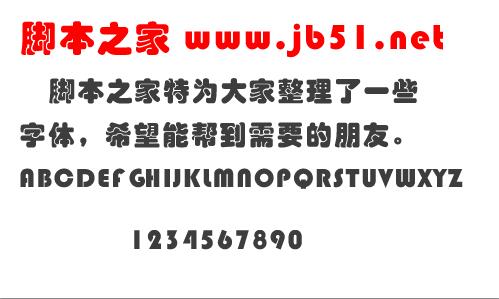
微软简琥珀体
微软简琥珀字体是一款十分好用,且非常漂亮的中文字体,字体拥有结构方正均衡、字形饱满圆滑、笔画特点丰富等优势,也显得字体在充满灵动沉稳元素的同时,又不失优雅,适应于报纸和杂志和书籍中常用字体海报、个性促进品牌标志设计、字体设计、文本装潢、信息展示、篆刻制模英文、数据制作、装潢设计、视觉设计、字帖等一切合法应用场景,有喜欢的朋友可免费下载收藏。